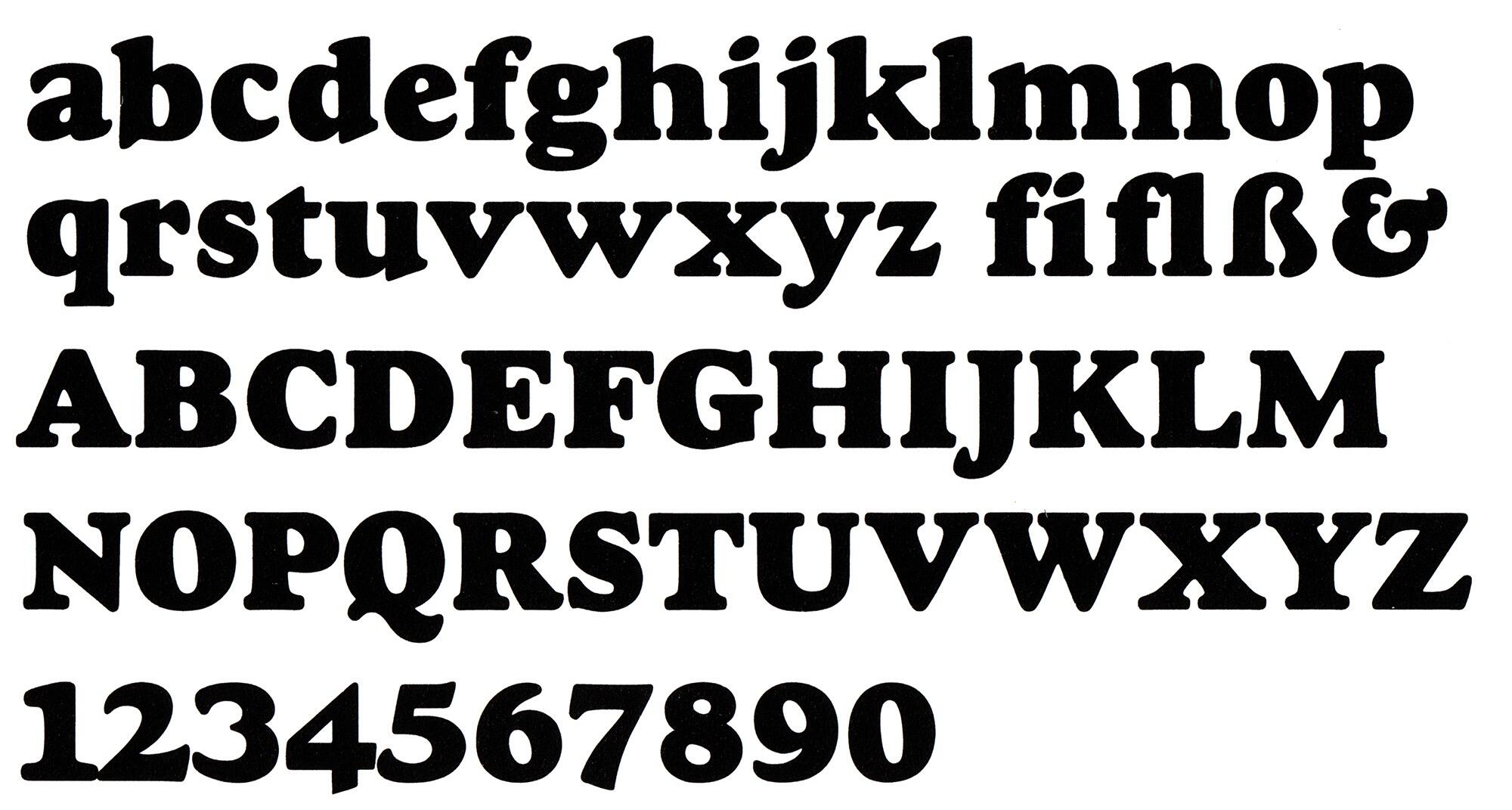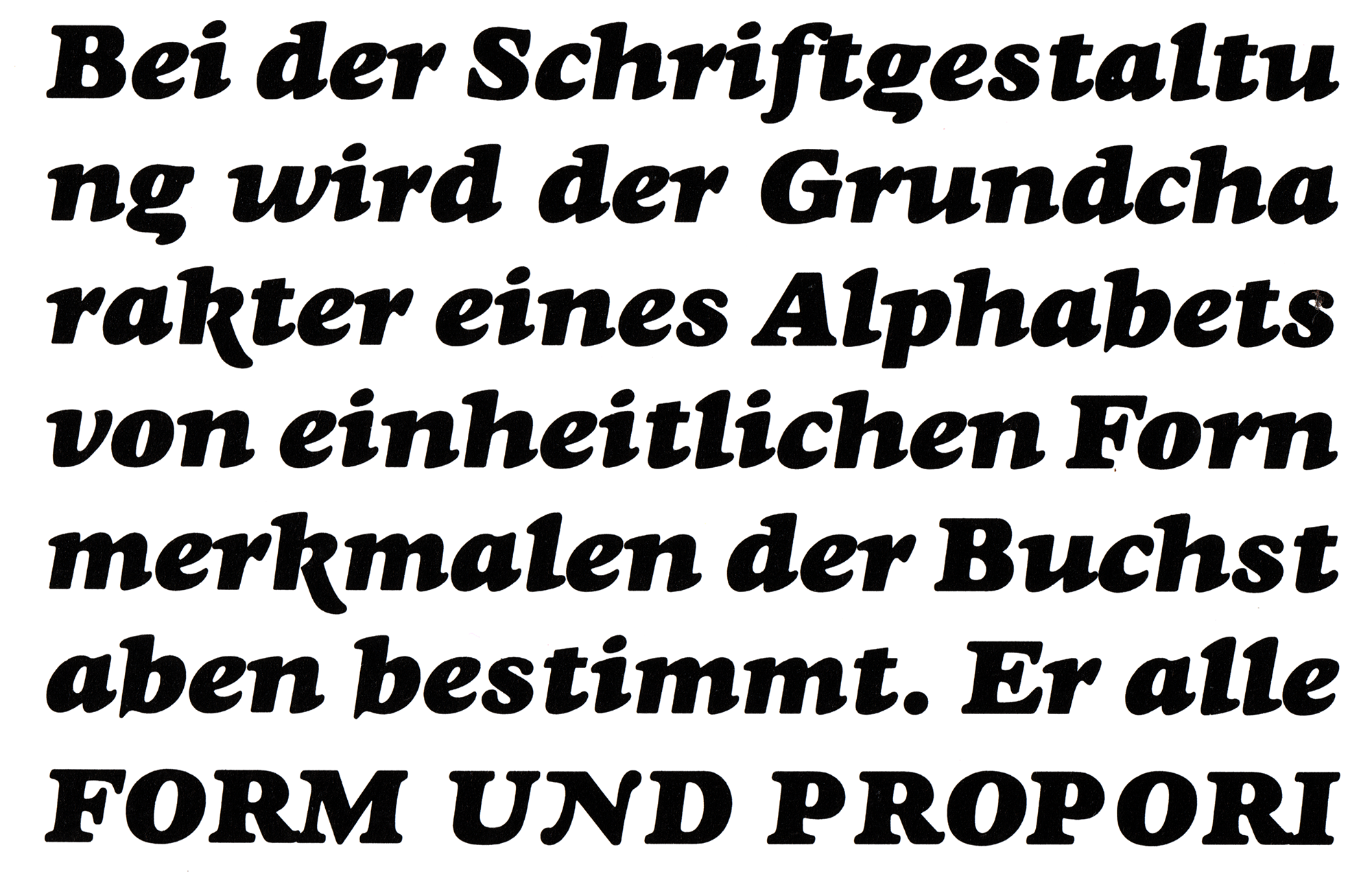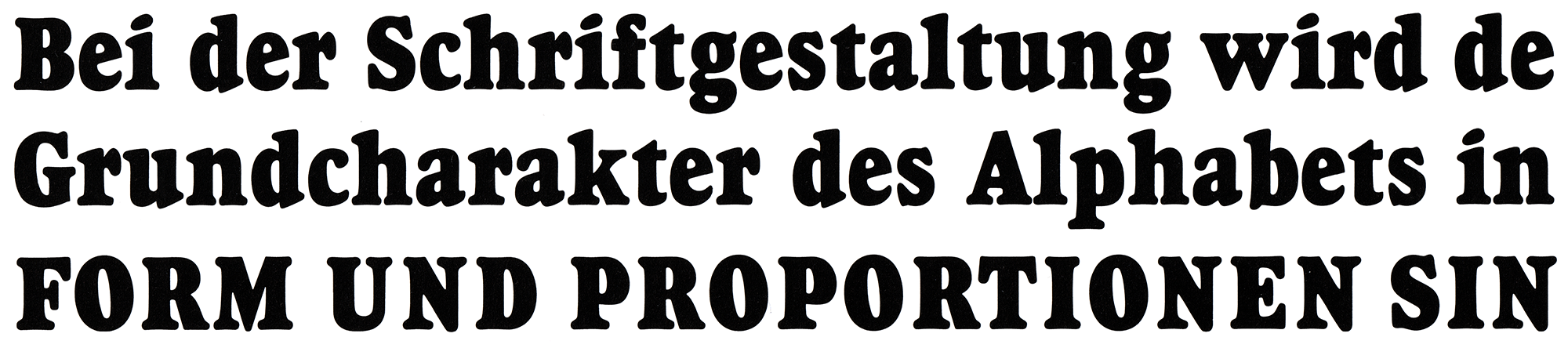
- 1925
- Antiqua dekorativ
Die Goudy Heavyface erschien 1925 by Lanston Monotype und nach der äußerst erfolgreichen Cooper Black (1922) in ähnlichem Stil. Es gab einen normale, einen kursiven und einen schmalen Schnitt, die später auch in den Fotosatz übernommen. Digitale Versionen sind heute von verschiedenen Anbietern verfügbar (P22, Linotype, URW, LTC, Scangraphic, Tilde, Bitstream), meist jedoch nicht mit allen Schnitten und Zeichen des Bleisatz-Originals.